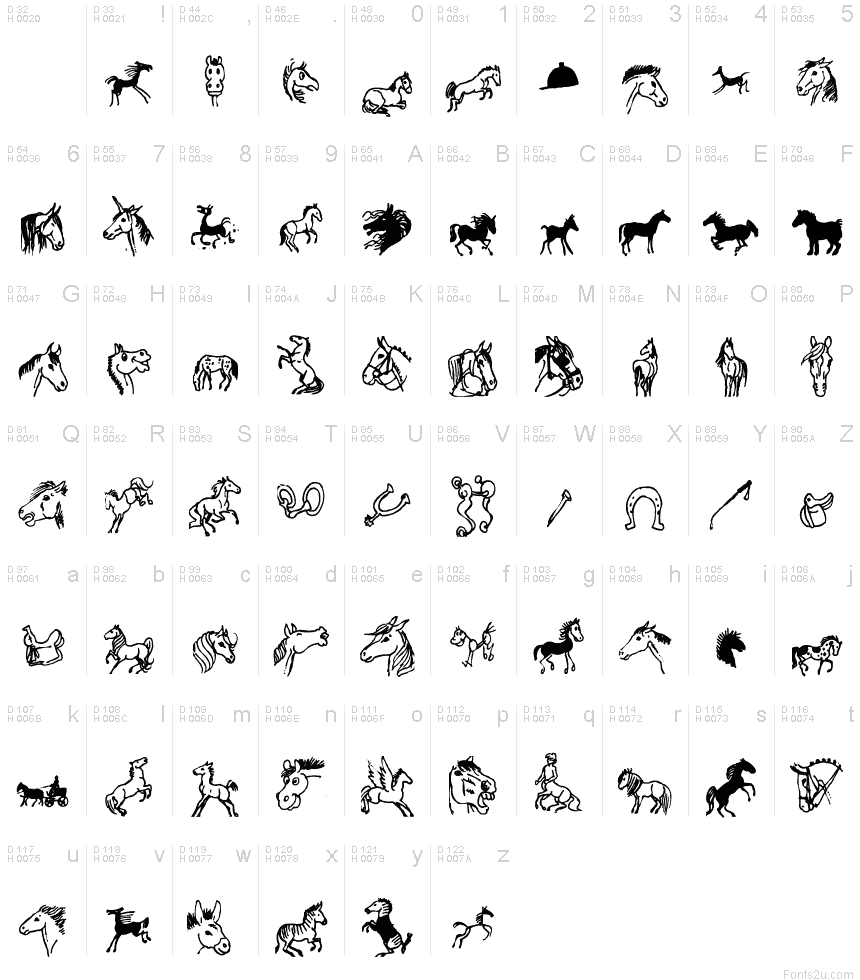
Il font Horsedings di Data Becker è un carattere dingbat gratuito che trasforma ogni battuta sulla tastiera in una vivace illustrazione equina. Dai pony al trotto alle sagome decise, fino agli unicorni e ai destrieri alati, ogni segno sembra disegnato a mano con linee leggermente irregolari, dall'effetto inchiostrato, che donano calore e movimento. Il mix di figure piene e scontornate ti offre un piccolo kit di strumenti visivi per creare bordi, badge o sequenze narrative senza dover ricorrere ad artwork personalizzati.
Con Horsedings puoi decorare rapidamente schede didattiche per bambini, inviti, volantini per maneggi, loghi, adesivi e pagine di scrapbooking. Lo spessore costante del tratto mantiene l'insieme visivamente armonioso, evitando che la ripetizione delle icone risulti caotica. Questo font gratuito si presta perfettamente a essere utilizzato in grandi dimensioni e abbinato a un carattere sans serif geometrico e pulito, lasciando che le illustrazioni giocose facciano risaltare la personalità senza compromettere la leggibilità del testo.